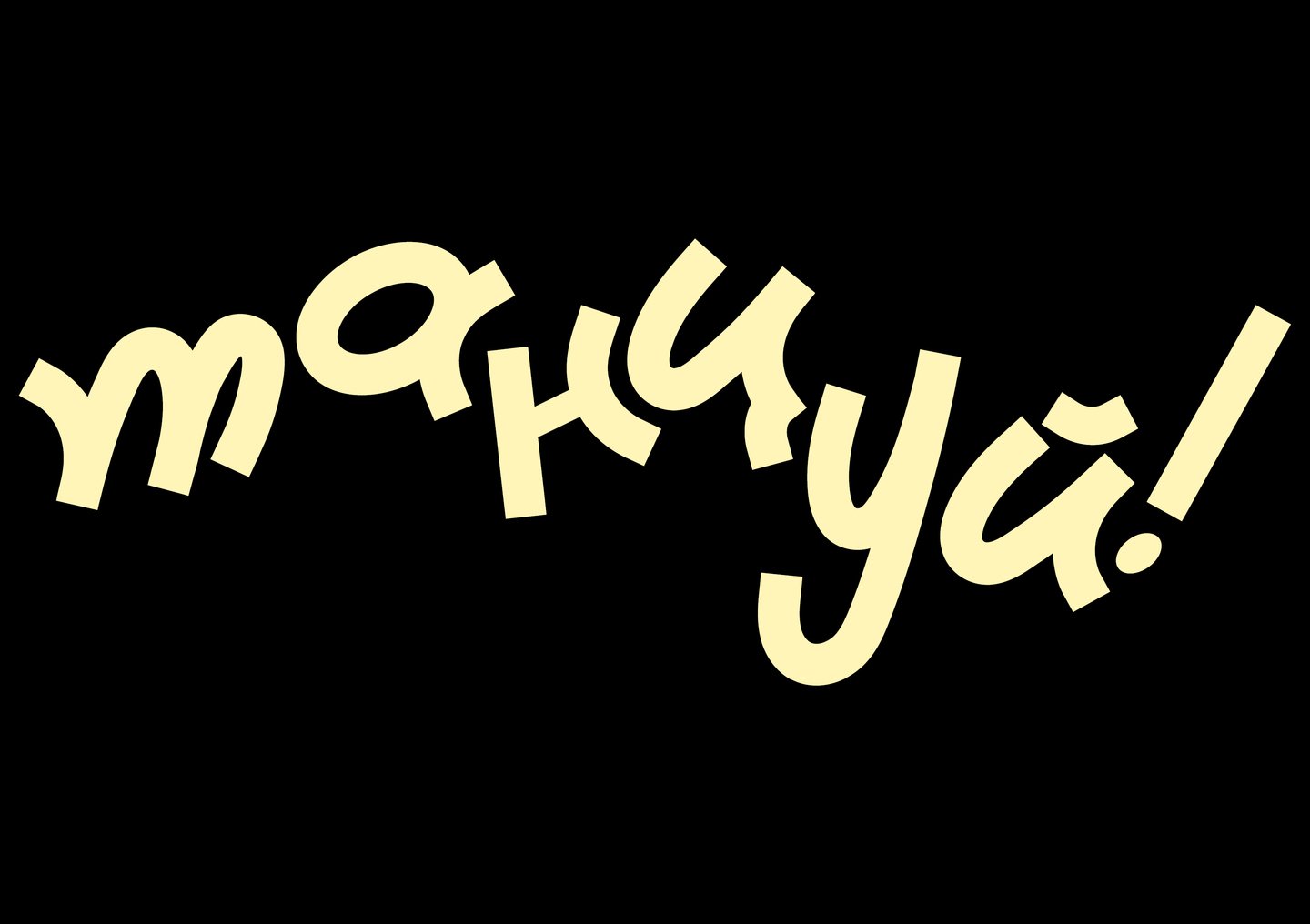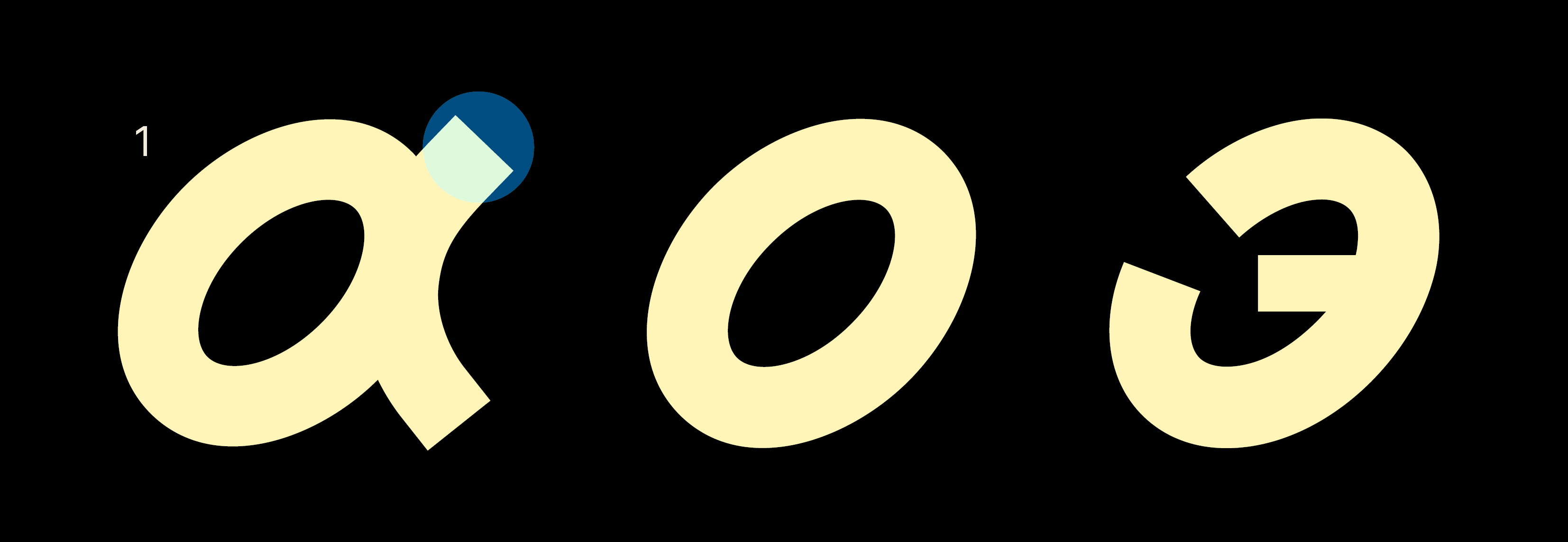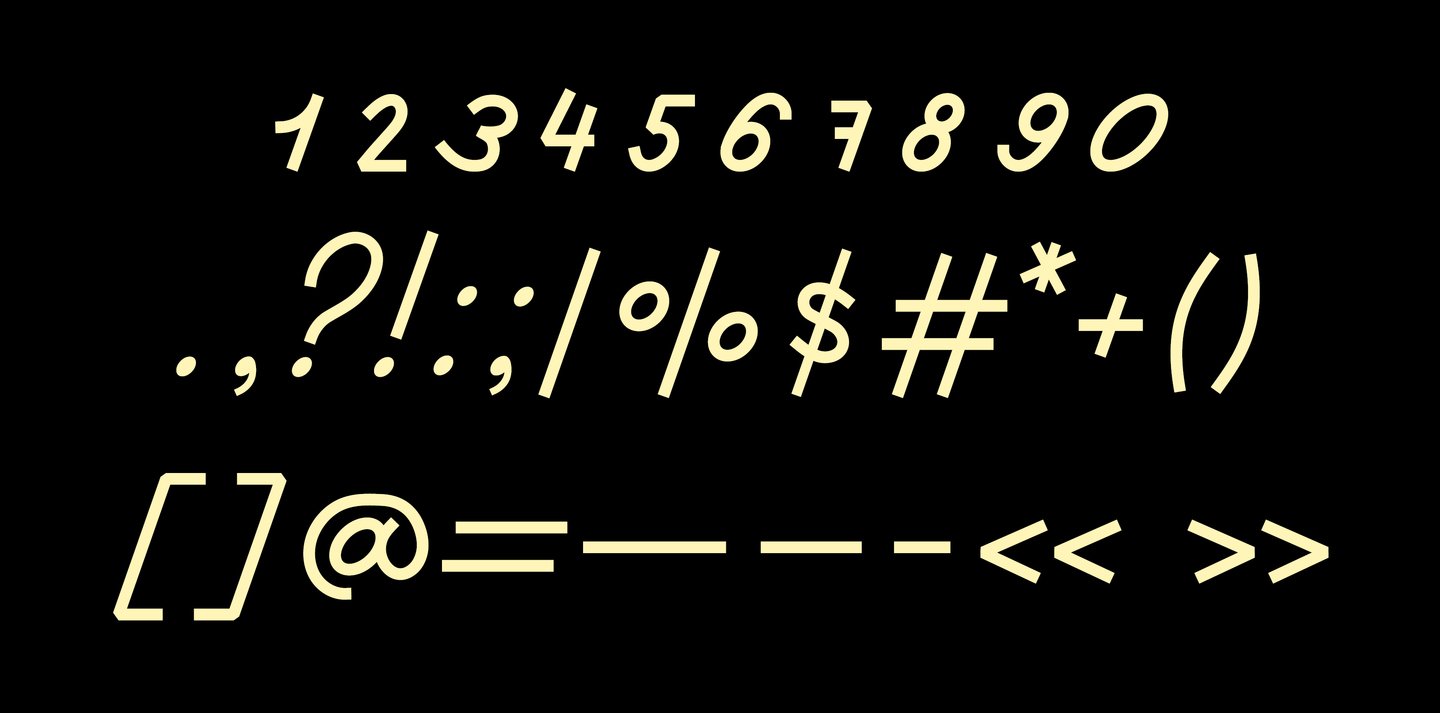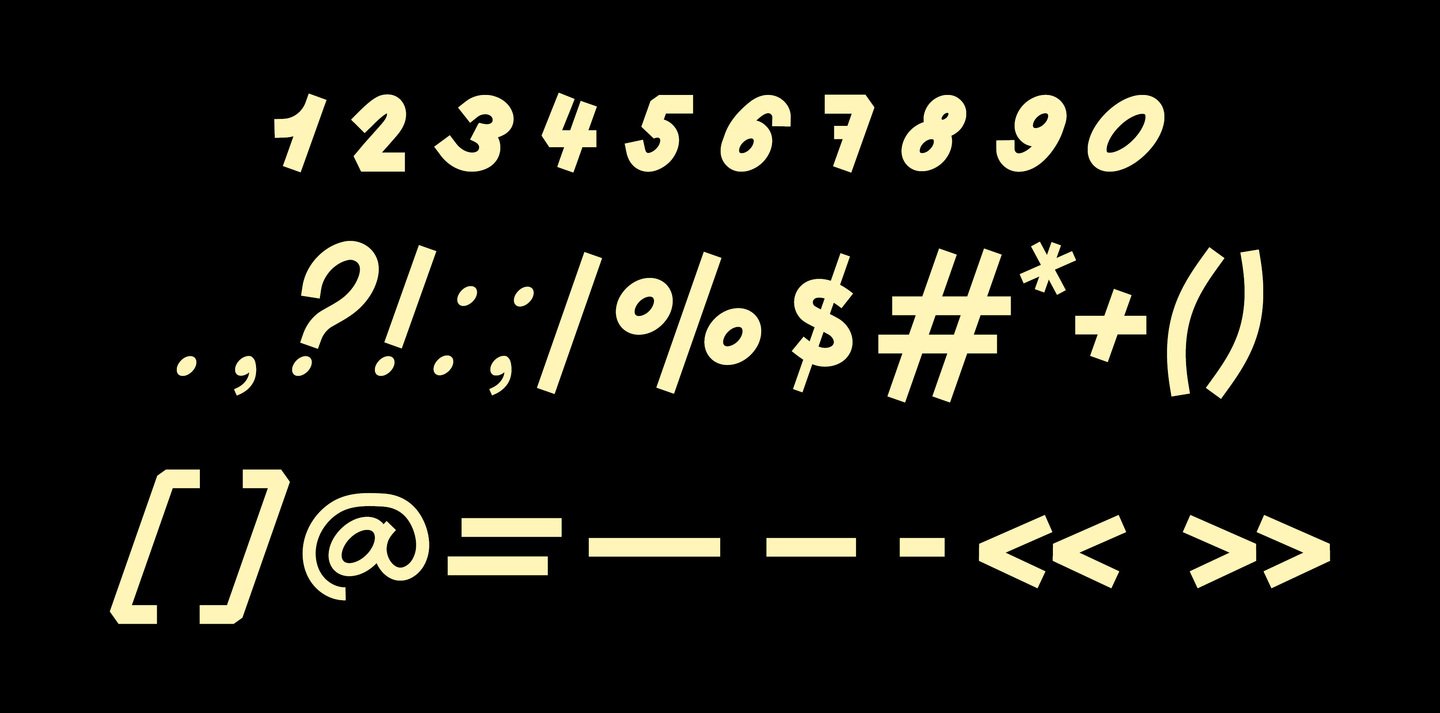
dance step font
dance step — шрифт вдохновленный эстетикой фильма «Шаг вперед» и хип-хоп танцев
В основе — динамика движения, ритм хип-хопа и пластика человеческого тела. Характер начертаний отражает импульсивность и свободу уличного танца
Особенности шрифта:
1 — терминалы под углом 2 — наклон овалов 45° 3 — мягкий контраст между штрихами
кириллица
кириллица. второе начертание
латиница
латиница. второе начертание